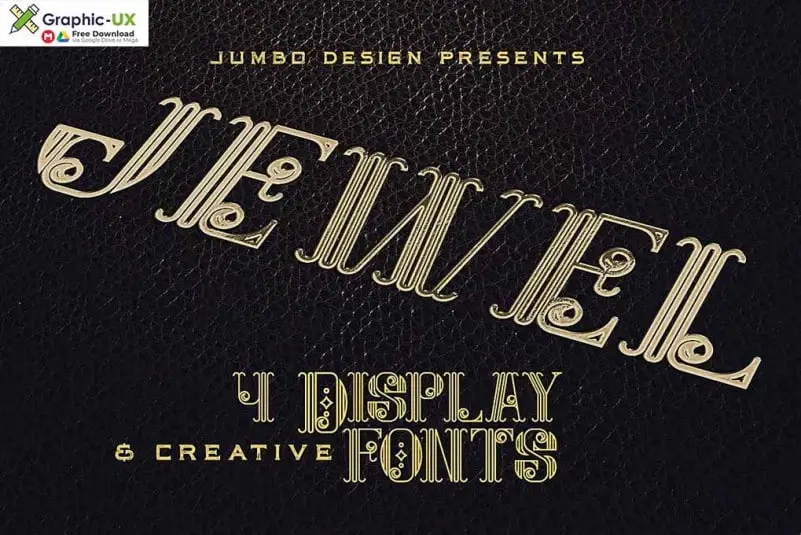
Jewel – Display Font – Download Grátis
Jewel – Display Font é uma fonte customizada com quatro estilos distintos que transmitem uma experiência vintage ou retro, sendo perfeitamente adequada para criações de design único e moderno. Criado pelo designer guxjohn, Jewel oferece um caráter sério em sua versão regular e uma vibe mais desorganizada na sua grunge. Ademais, a fonte possui um estilo forte em suas versões bold e bold grunge, que traz um toque de irreverência ou desprendimento dependendo da utilização. Essa variedade permite ao designer adaptar o texto para se adequar perfeitamente ao contexto do projeto, seja ele editorial, tipográfico ou até mesmo em publicidade, garantindo uma experiência visual única e atraente. Este é um excelente recurso para aqueles que procuram personalizar seu design com uma fonte vintage que não só transmite um tom memorável, mas também oferece um grau de flexibilidade que pode se adaptar a vários ambientes de design.